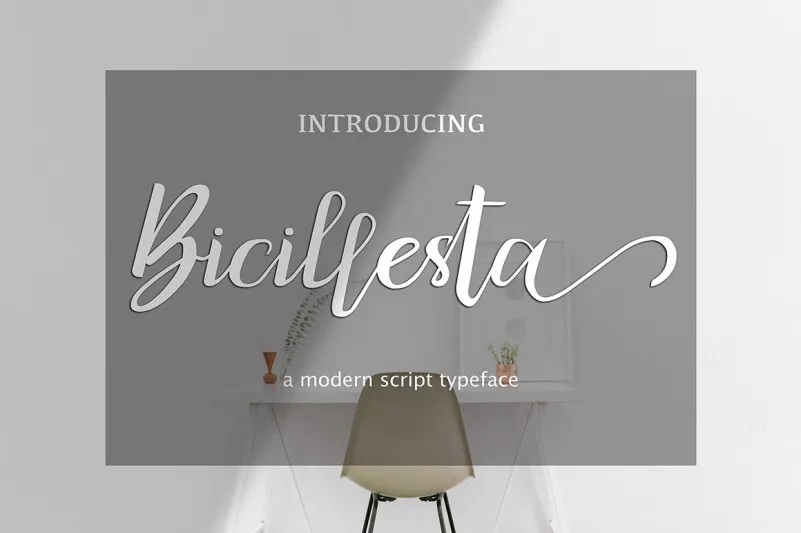
Bicillesta Calligraphy Font – Download Grátis
Introduzimos a Bicillesta Font. Esta é luxuosa em seu estilo casual e distintivo, perfeita para suas criações de marca, caracteres decorativos e linhas bailarinas! Ela foi projetada e compartilhada pela hikhstudio e representa uma nova tipografia script moderno. A Bicillesta Calligraphy é perfeita para logos elegantes, embalagens luxuosas, estacionários de casamento, websites e qualquer outro projeto que exija um toque manuscrito e de alto luxo. Incluímos alternativas e ligações, permitindo-lhe dar aos seus logotipos ou nomes um olhar único, como se fossem escritos à mão. Este arquivo está disponível no formato ttf, onde pode instalá-lo em sua PC ou OS.